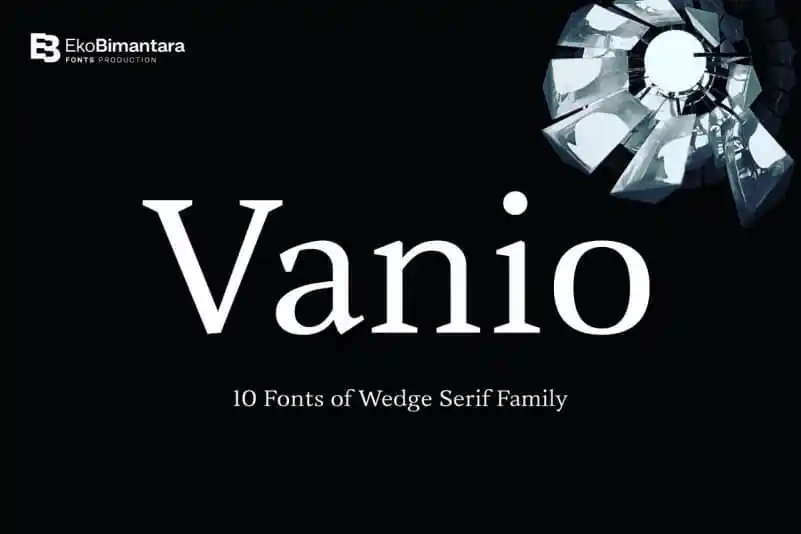
A Vanio Trial Serif é uma família de serifos moderna que combina elegância com modernidade. Sua estética única é perfeita para aplicativos onde a feminilidade e a sofisticação são valorizadas, como logomarcas, assinaturas de moda ou designs editoriais. Este tipo de fonte traz um contraste leve e claro, resultando em letras elegantes com uma largura mais espaçada em estilos rectos, além de ter um contraste médio e traços caligráficos característicos. Suas letras são ajustadas para o reconhecimento óptico e a padronização versátil, atendendo a diversos tipos de tipografia. A Vanio Trial Serif oferece uma grande variedade com 10 estilos, desde o regular até a extrabold, cada um acompanhado de suas itálicas correspondentes. Seus mais de 460 caracteres são ideais para suportar uma ampla gama de idiomas latinos e contêm recursos OpenType como ligação de caracteres, números do tipo antigas, fracionários e outras variações de caracteres. Uma ótima opção para designers que valorizam tanto a modernidade quanto o charme tradicional em seus projetos.